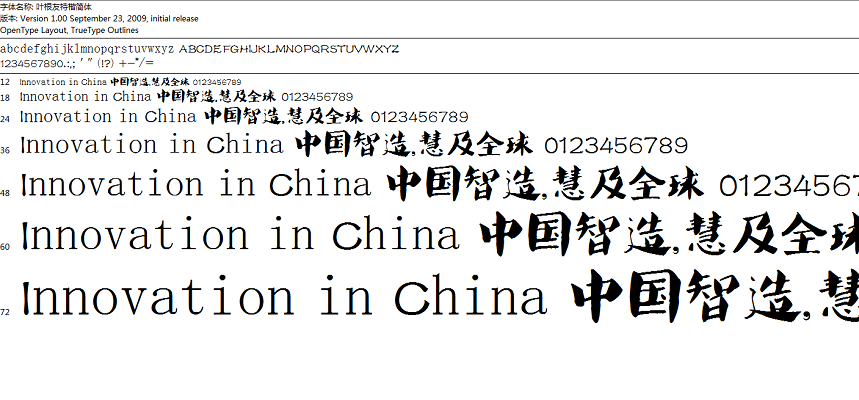
叶根友特楷简体
叶根友特楷简体是一款极具特色的楷书字体,该字体刚劲有力,规正质朴,是力与美的完美结合,给人一种威严肃穆的感觉,喜欢这款字体的朋友们快来绿色资源网下载体验吧!
叶根友特楷简体是由叶根友开发设计的一套风格独特的楷书字体,区别于传统书法楷书的中规中举,在笔画运笔以及起笔等方面均有创新性的突破。笔法刚劲规正,风格质朴,有如刀锋遒劲,结合了柳体、颜体、欧体的不同风格而书写的一套叶根友特楷体字库。